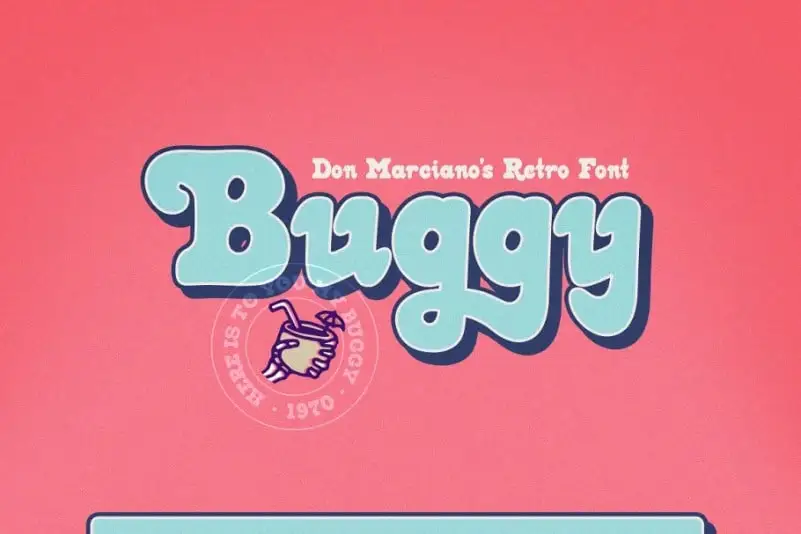
Buggy Display Font – Download Grátis
A Buggy Display Font é uma escolha perfeita para quem busca um estilo inovador e moderno em seus projetos gráficos. Inspirada nos estilos de design dos anos 60 até os anos 80, esta fonte apresenta letras maiúsculas e minúsculas, inclusive alternativas maiores, com todas as casas de pontuação padrão e caracteres internacionais para suportar múltiplos idiomas. O design contém uma leve tendência contemporânea, combinando elegância com formas serifadas fortes e ângulos trabalhados a mão. Com espaçamento entre os símbolos cuidadosamente ajustado, esta fonte será um complemento ideal para qualquer projeto de design, criando um visual atento e único.